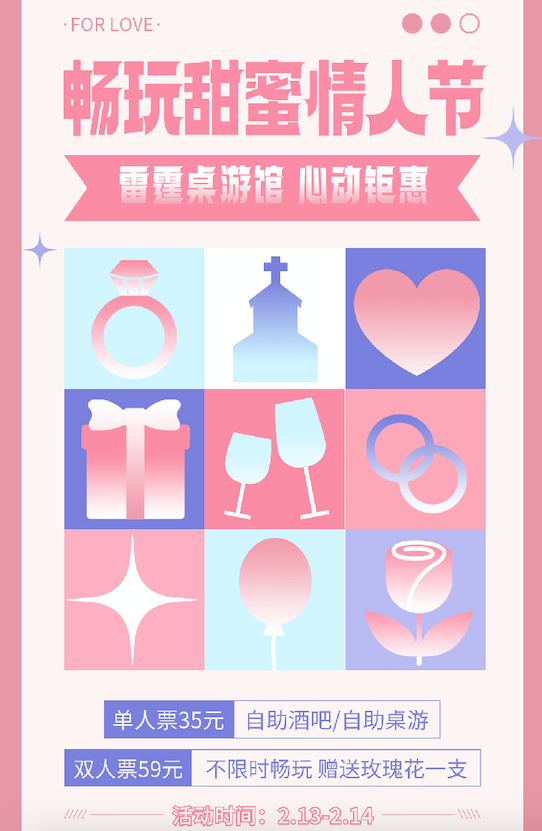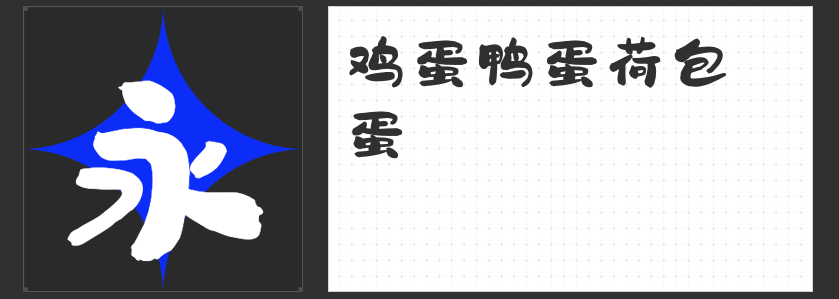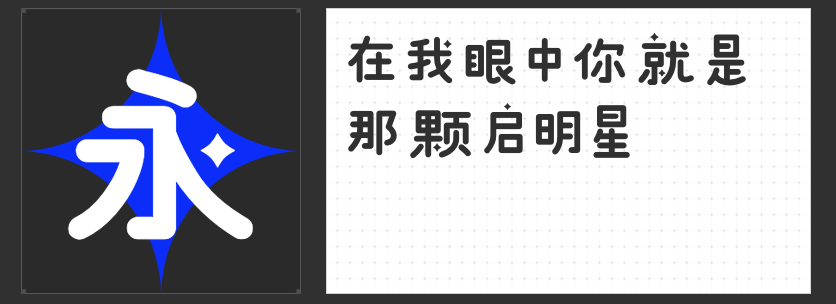
探索个性之美:高手兵克系列字体推荐
在这个视觉为王的时代,字体不仅是文字信息的载体,更是个性与情感的直接表达。今天,就让我们一同走进高手兵克系列字体,感受它们独特的魅力与韵味,为你的设计、文案或日常书写增添一抹不可复制的风采。
1.高手兵克星耀体
这款字体如同夜空中最亮的星,璀璨夺目。其笔画流畅而有力,每一个字都仿佛蕴含着星辰的光芒,适合用于需要突出主题、吸引眼球的场合,让你的作品在众多设计中脱颖而出。
2.高手兵克侠客体
侠义精神,自在其中。侠客体以其独特的笔触设计,展现出一种不羁与洒脱,既有传统书法的韵味,又不失现代设计的简洁明快。它适合用于武侠、江湖风的宣传海报或游戏界面,让人一眼便能感受到那份快意恩仇的豪情。
3.高手兵克笨笨体
别看名字中带着“笨笨”,实则是一种大智若愚的可爱。字体结构周正而不失松弛,点画圆润,整体风格自由率真、活泼灵动,仿佛每个字都在跳跃,传递着轻松愉悦的氛围。它非常适合儿童读物、卡通形象包装或是轻松愉快的网络内容,让人在阅读时也能感受到温暖与乐趣。
4.高手兵克雷霆体
雷霆万钧,势不可挡。这款字体以其强烈的视觉冲击力和力量感著称,笔画粗犷而不失秩序,如同闪电划破夜空,震撼人心。适用于体育竞技、动作电影宣传或需要展现力量、速度与激情的场合,激发观众内心的热血与激情。
高手兵克系列字体,每一款都是对个性与美感的极致追求。无论你是设计师、文案高手还是文字爱好者,都能在这系列字体中找到属于自己的那份独特表达,让每一次创作都成为一次心灵的旅行。